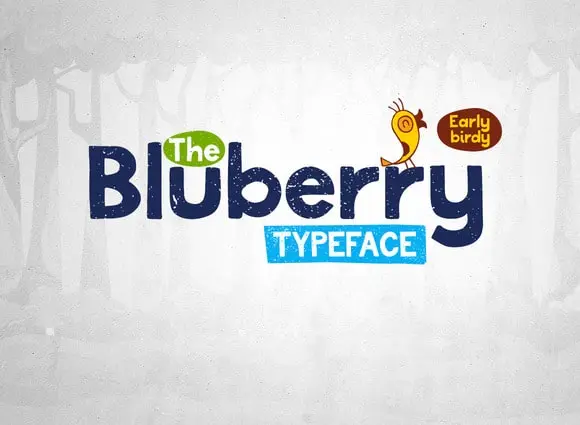
A Bluberry Typeface é uma fonte Display criada por Hamilton, disponível na CreativeMarket. Esta fonte premium foi originalmente vendida pela Squarepack, mas está gratuita para download hoje. Com traços suaves e coloridos, a Bluberry oferece um toque único e divertido que certamente dará um toque especial aos seus projetos digitais. Perfeita para o uso em títulos ou headlines, essa fonte traz vida ao seu design de forma vibrante e divertida. Seja você designer de sites, blogueiro ou até mesmo criador de materiais publicitários, a Bluberry oferece uma maneira única de destacar seu conteúdo. Não perca esta oportunidade gratuita de adicionar um toque especial à sua próxima criação!